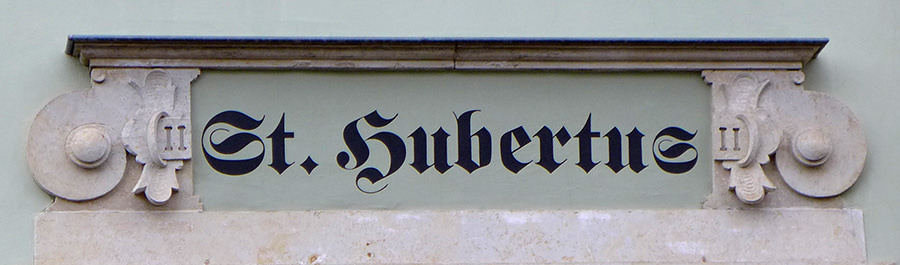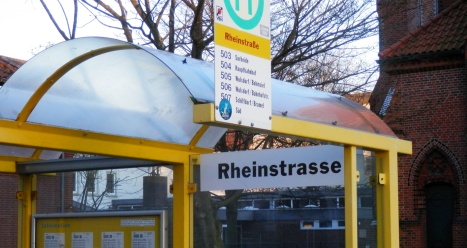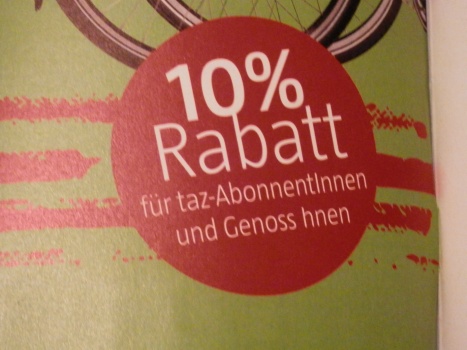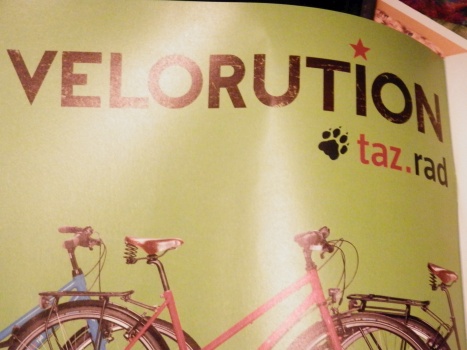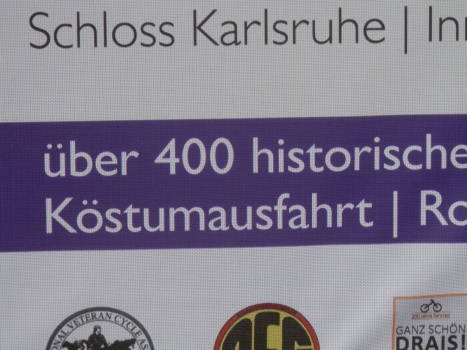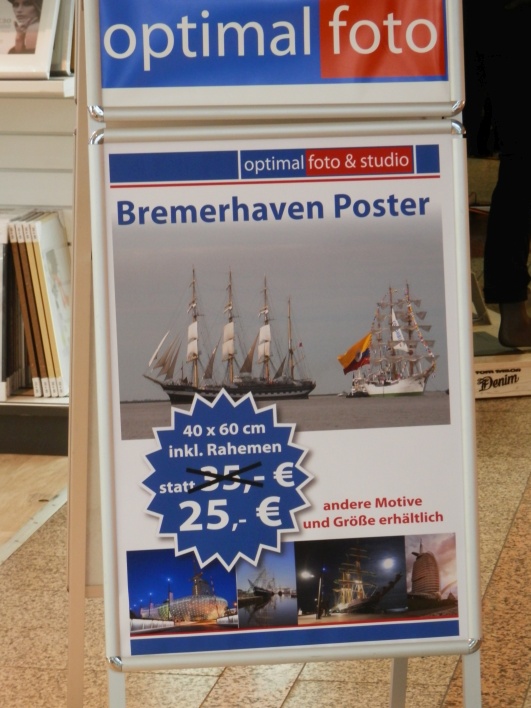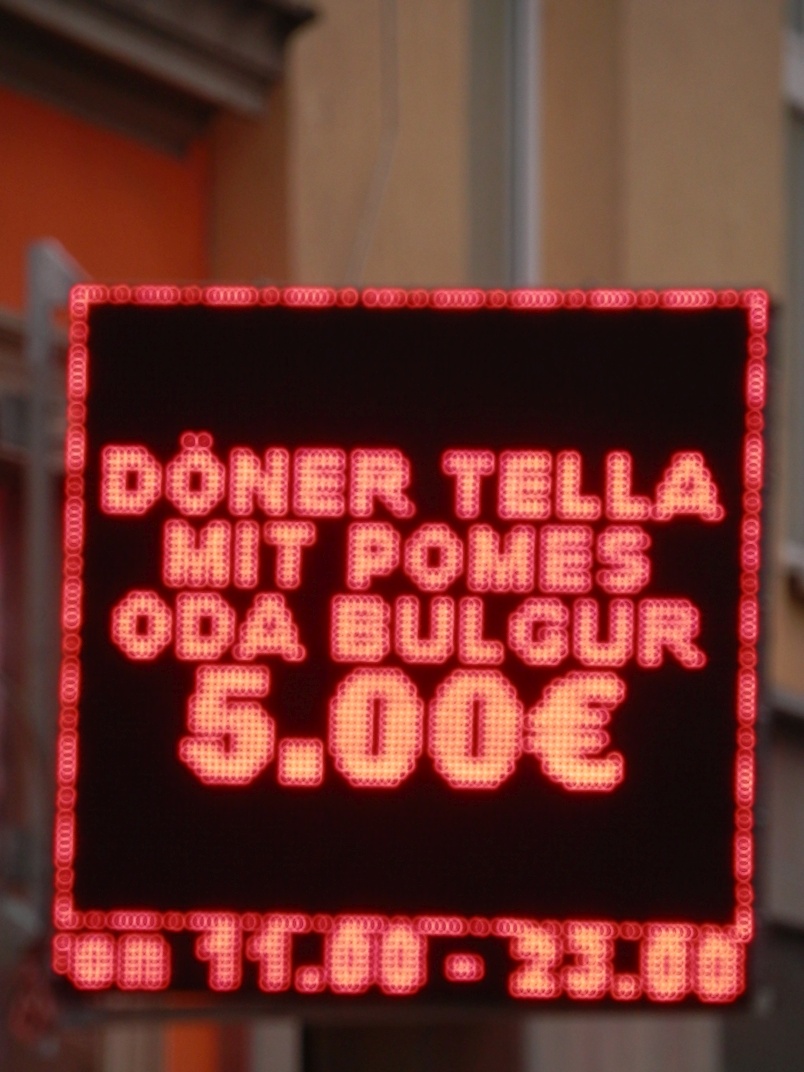
Neue Rechtschreibung?
Vielleicht sowas wie Voß's Trasse?
Des Rhein(e)s Trasse hat aber in Bremerhaven nix zu suchen! Das ist Weserland! Und sollte der Rhein doch mal dort vorbei kommen, ist wohl erhebliches schiefgeflossen ...
Dabei hätte der Schildermaler nur das andere Schild lesen müssen ...
Hier jedenfalls ein weiteres Bsp. für diese Sorte Haltestellenschilder ...
Heute die neue Zeitschrift des VCD aufgeschlagen und gleich auf S. 2 eine Annonce:
Nachdem nun auch Kuba mit dem Klassenfeind kolaboriert, kann man die Buchstaben ja ruhig ein weing herumwürfeln ...
Viel interessanter ist aber, wer alles Rabatt kriegt:
Ich stolperte eben in einer TV-Doku über den eingeblendeten Geburtsort "Laugßargen".
Eine kleine schnelle Wikipediarecherche führte mich tletztlich zur Liste deutscher Bezeichnungen litauischer Orte, wo es im memelländischen Teil eine ganze Reihe von Orten gibt, die es dort wahlfrei mit sz oder ß gibt.
Ist dieses ß nach Konsonant eine dortige lokale Eigenart (gewesen)?
Ich stolperte eben in einer TV-Doku über den eingeblendeten Geburtsort "Laugßargen".
Eine kleine schnelle Wikipediarecherche führte mich tletztlich zur Liste deutscher Bezeichnungen litauischer Orte, wo es im memelländischen Teil eine ganze Reihe von Orten gibt, die es dort wahlfrei mit sz oder ß gibt.
Ist dieses ß nach Konsonant eine dortige lokale Eigenart (gewesen)?
Es sieht stark danach aus, dass ein solches ß (sowie ein Sz am Wortanfang) genau dann genutzt würde, wenn im Litauischen ein ž genutzt wurde, es also eine systematische Transkription darstellt.
Interessanterweise steht das ž im Litauischen für das stimmhafte sch ([ʒ]⁠) und nicht für das stimmlose s () wie im Deutschen. Eventuell stammt dies aus Frakturzeiten und hierfür wurde explizit ſz statt ß genutzt.
Irgendwie sieht das elektronisch montiert und wenig echt aus … :-?
Ich habe mal gelernt, dass es nicht nur die beiden s gab, sondern auch ein richtig rundes Schluss-s, das im Prinzip die Form des S hat aber definitiv nur am Wortende steht*. Vielleicht gab es auch eine Vorlage die der Art gestaltet war und man hat es da abgeguckt?!
* So ad hoc habe ich jetzt natürlich keine Quelle gefunden – sogar den Bollwage habe ich durchgeblättert :-o;-)
Und ich hätte da mal eine neue Rechtschreibung als Font gebaut. Unbedingt mit OpenType-Fähiger Software testen!
und zu dem hier: Ja, das hätte dann auch wirklich Döna heißen müssen, ebenso Bulgua, wie kann bloß so ein Fehler passieren? -
Oh schiet, "a" für er im Auslaut muss ich da in meine Schrift unbedingt noch rein bauen...
Echt schlimm!
Das heißt doch Döna!
Um's Eck kam heute meine Tageszeitung Badische Neueste Nachrichten mit einem Artikel, in dem es auch um die Braune Hundez-
ecke ging ...
Ich habe jetzt vier Anläufe gebraucht, um den Fehler zu erkennen. Es wird Zeit für den Feierabend.
Bin heute in einem 13 Jahre alten Schlussbericht über
"140.000 sozialversuchungspflichtig Beschäftigte"
gestolpert, die es damals hierzustadt gegeben haben soll ...
Sogar Google findet paar Fundstellen des Wortes, scheint also ein bei dem Programmierern von Autokorrekturen ein beliebtes Wort zu sein ...:mrgreen:
Ich hatte mal einen Bekannten der Mercedes-Benz-PKW-Bedienungsanleitungen (:biglove:) schrieb und vor dem Druck-PDF erstellen die Autokorrektur drüber laufen lies und dann die Daten in die Druckerei sandte. Resultat: Meerhechtes-Benz. 🤐
Diesen Dialog aus einem anderen Forum,  will ich euch nicht vorenthalten:
A: Wenn nicht, kann ich es aus der Vögelperspektive betrachten und auch händisch selbst machen.
B: Dringende Bitte um "Aufklärung" dieses Begriffes 😀
A: Ich mache bei dem verquasteten Schulmeisterquatsch nicht mit. Außer Pinguinen können fast alle Vögel von oben herab schauen, nicht nur einer. Es heißt ja auch nicht Hundhaufen 😛
Es ging natürlich nur um das Einparken mit Kamerahilfe, nicht um das, woran bestimmt x % ...
Aber ganz unrecht hat er nicht Hundhaufen/Vogelperspektive oder eben Hundehaufen/Vögelperspektive ...
Wobei der Hundehaufen seltenst von mehreren Hunden fabriziert wird ...
Nee, auch die nicht. Mehrere Hundehaufen werden von je einem Hund produziert, nicht von mehreren Hunden. "Von mehreren Hunden" würde bedeuten, dass mehr als 1 Hund an der Herstellung eines einzelnen Haufens beteiligt wäre.